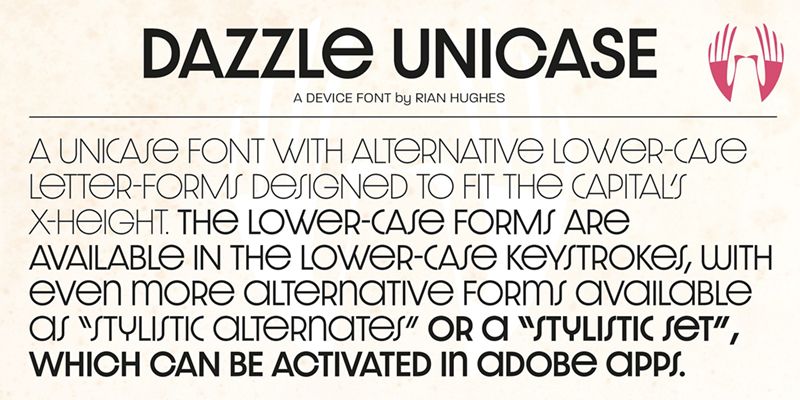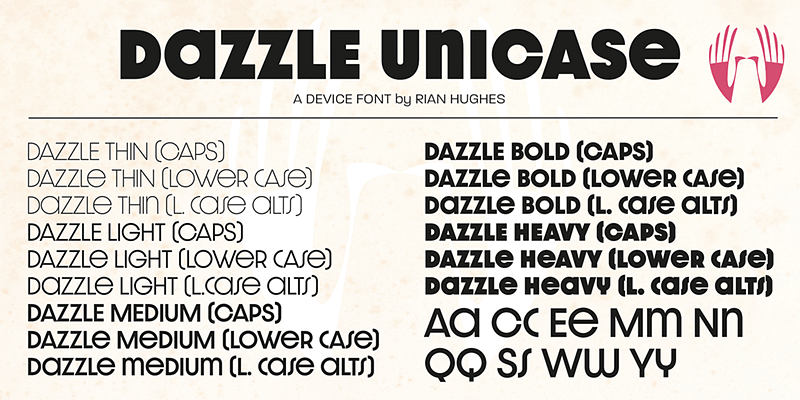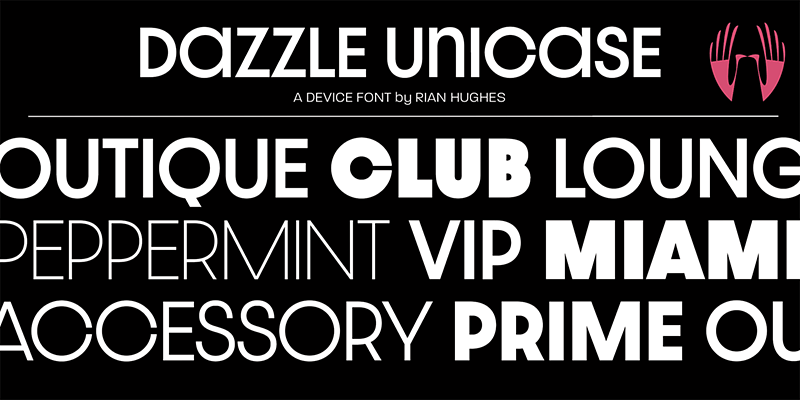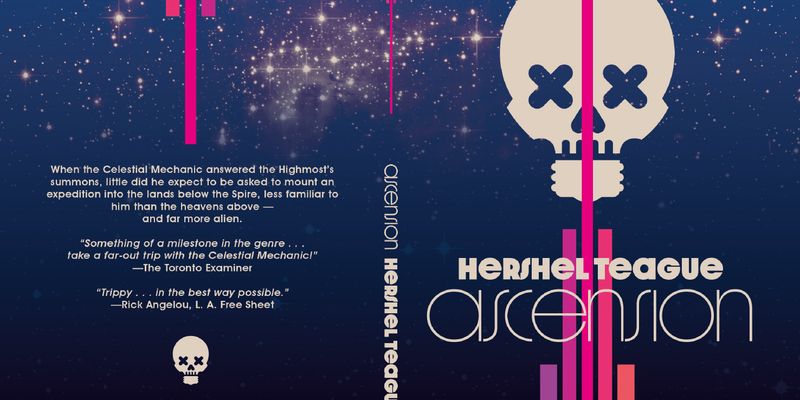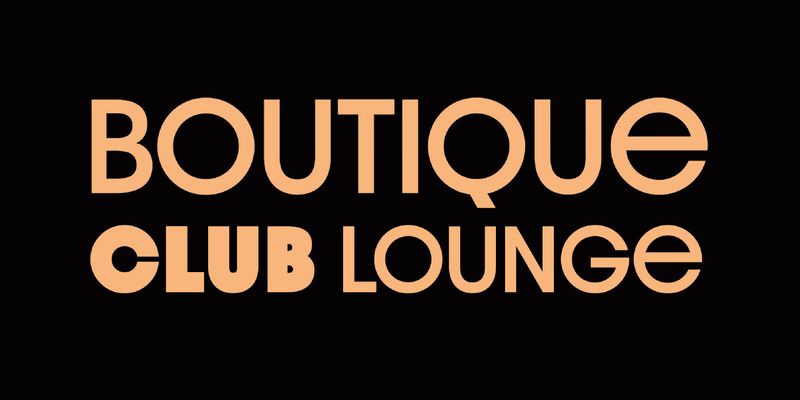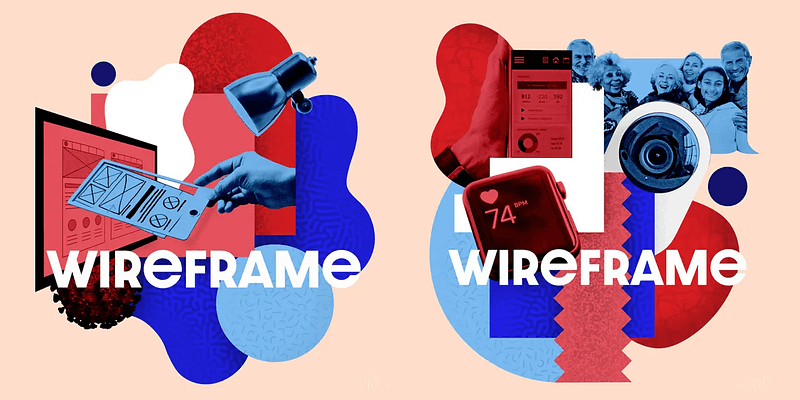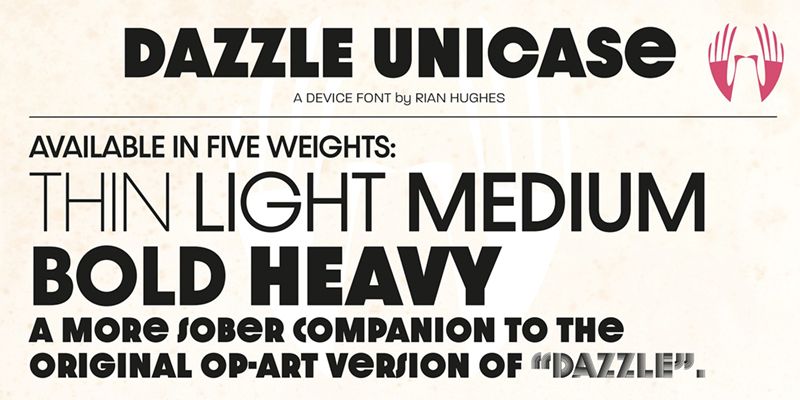
Dazzle Unicase es un elegante tipo de letra ajustado con formas de letras minúsculas que coinciden con la altura de x de la mayúscula, con más opciones disponibles como Opentype. Limpia, nítida y con estilo.
Tipo, diseño e imagen del ilustrador y tipógrafo inglés Rian Hughes.